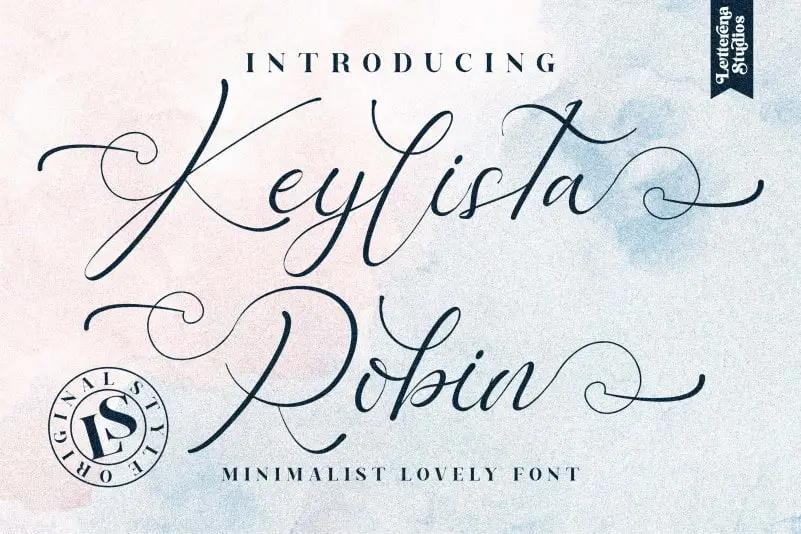
Keylista Robin Calligraphy Font – Fonte Grátis
Keylista Robin Calligraphy Font
A Keylista Robin Calligraphy Font é uma tipografia feita à mão com linhas finas e estilizadas que brilha em todas as aplicações onde você precisa de uma toque humano. Perfeita para cartões de casamento, cartões de agradecimento, frases, cartões de boas-vindas, logotipos e cartões de negócios, ou qualquer outro design que requer um toque autêntico do pincel. Este font é PUA codificado, o que significa você pode acessar todos os caracteres e círculos com facilidade. Esta fonte vem repleta de estilo e personalização para dar ao seu projeto aquele ar a mais.